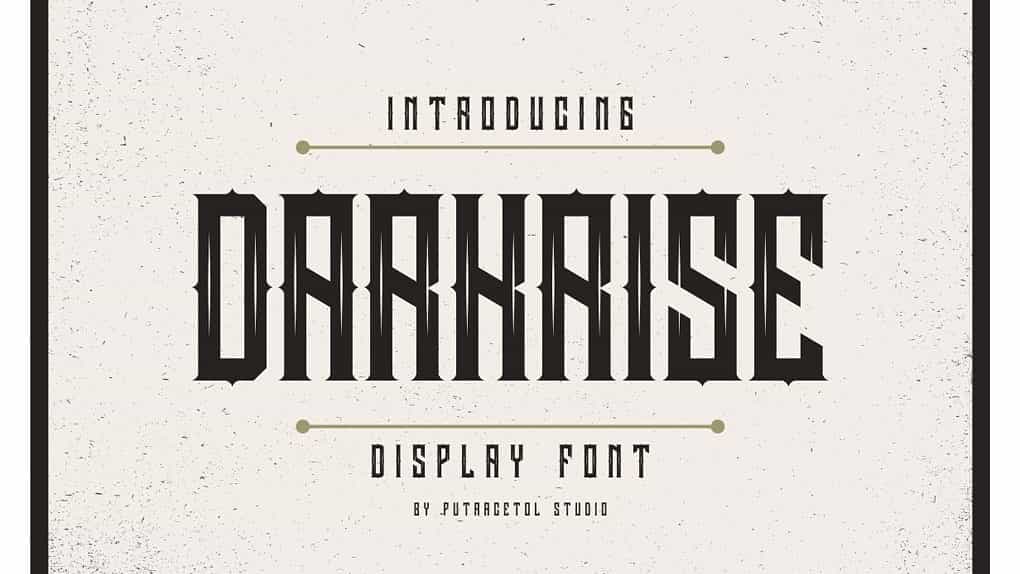
فونت انگلیسی کلاسیک برای تیتر Darkrise Typeface
فونت انگلیسی کلاسیک : این فونت انگلیسی با الهام از برخی حروف کلاسیک با لبه تیز. پویا، فلزی و پررنگ طراحی شده است. این نوع متن برای لوگو ، عنوان، برچسب، تیشرت، پوستر و … عالی است.